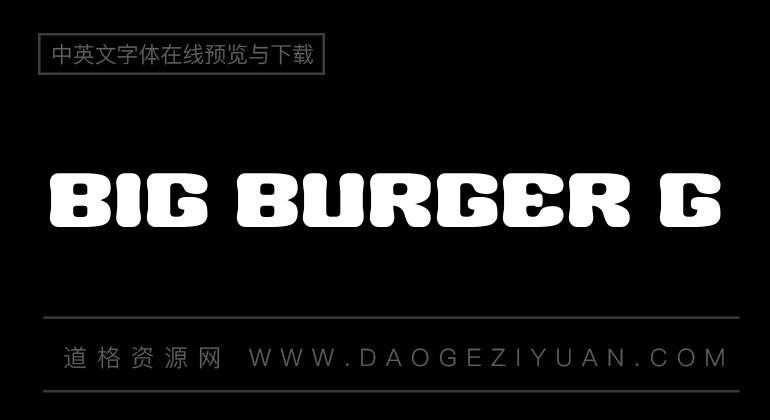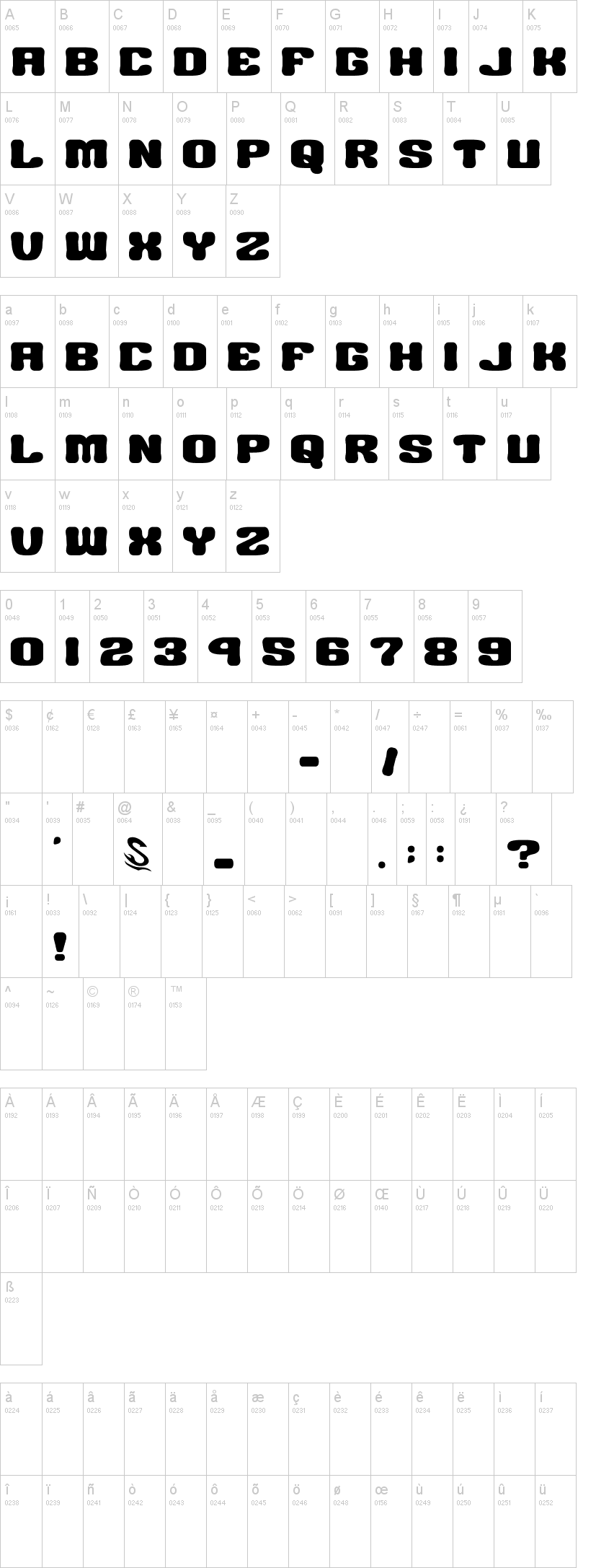
Big Burger G font is a bold, hand-drawn typeface created by the graphic designer, Graham Prentice. It features a unique, vintage-style look and feel, with a thick, rounded lettering style. The font is perfect for creating logos, headlines, and titles, as well as for adding a touch of personality to any design. The font is available in both regular and italic styles, and includes a wide range of characters and symbols.内容介绍
Big Burger G是一款非常不错的手写艺术字体,具有很好的视觉感,适合于文化类的宣传设计、商业类品牌的广告和产品包装设计以及个性化文字排版等较多场景。